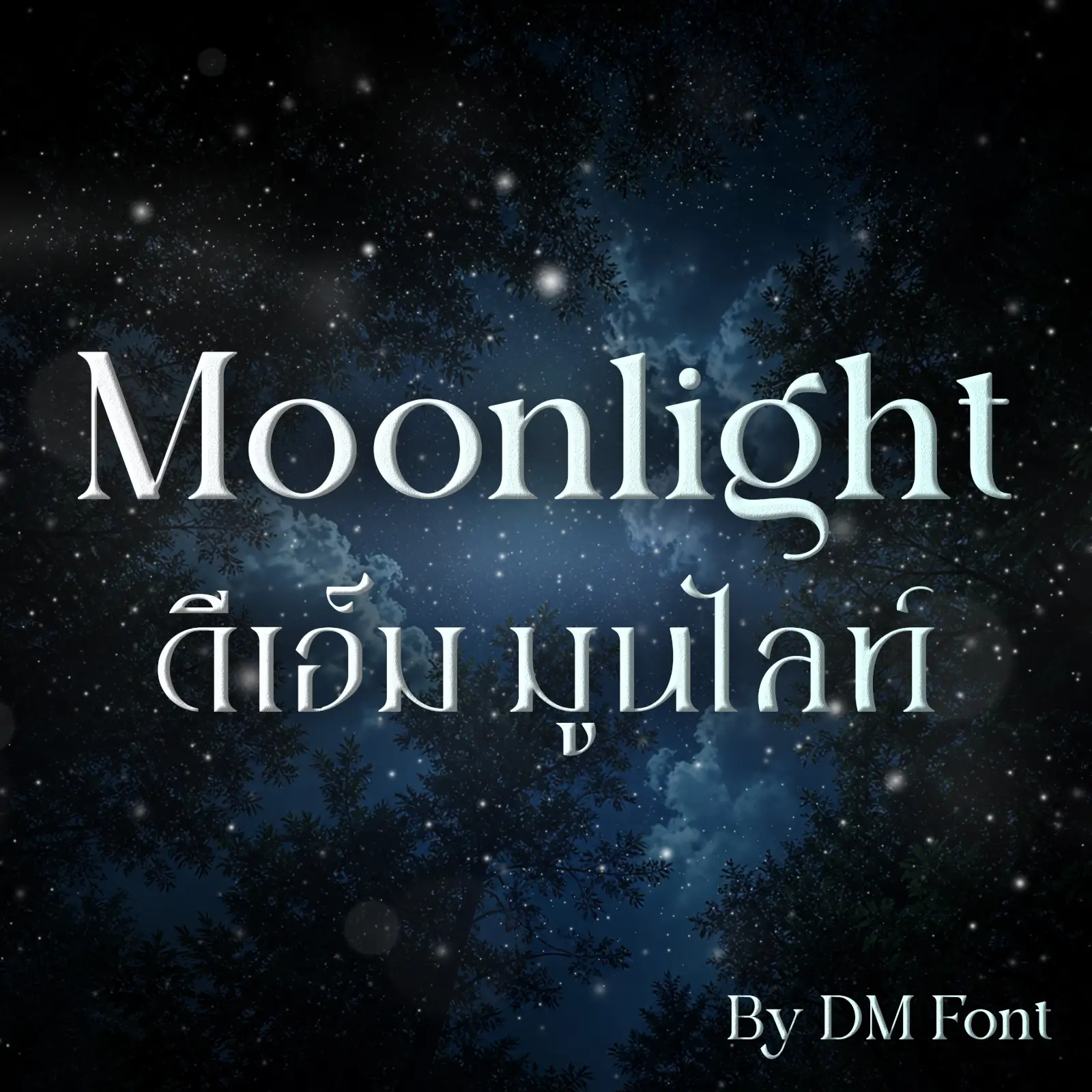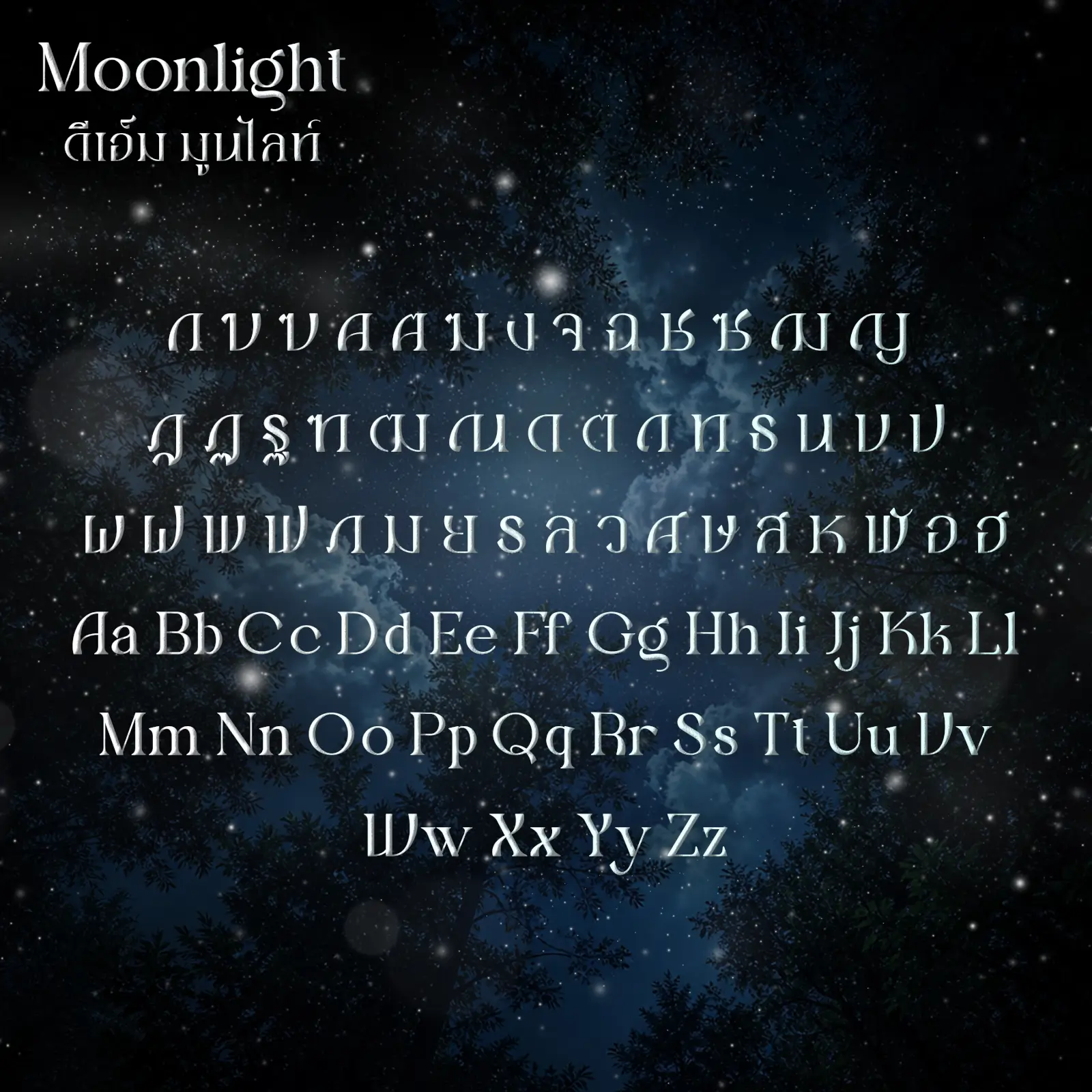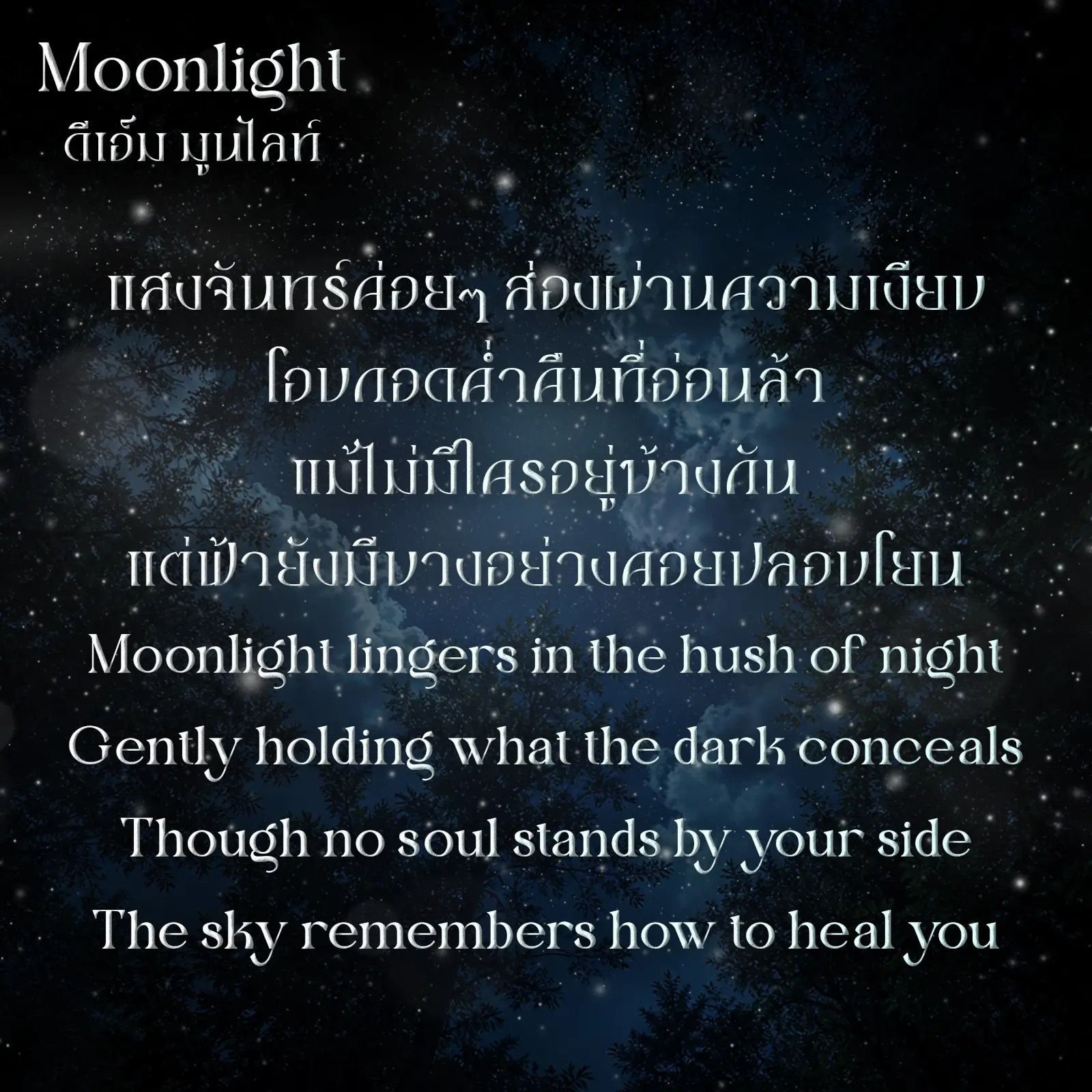
DM Moonlight (ดีเอ็ม มูนไลท์)
ฟอนต์ที่ออกแบบด้วยแนวคิดร่วมสมัย ผสานรูปทรงที่เป็นเอกลักษณ์เข้ากับจังหวะของตัวอักษรที่ลงตัว ให้ความรู้สึกทันสมัย ลึกลับ และมีมิติ เหมาะสำหรับงานออกแบบที่ต้องการสร้างอัตลักษณ์เฉพาะตัว ทั้งในงานกราฟิก งานสื่อ และงาน visual ที่เน้นบรรยากาศและอารมณ์